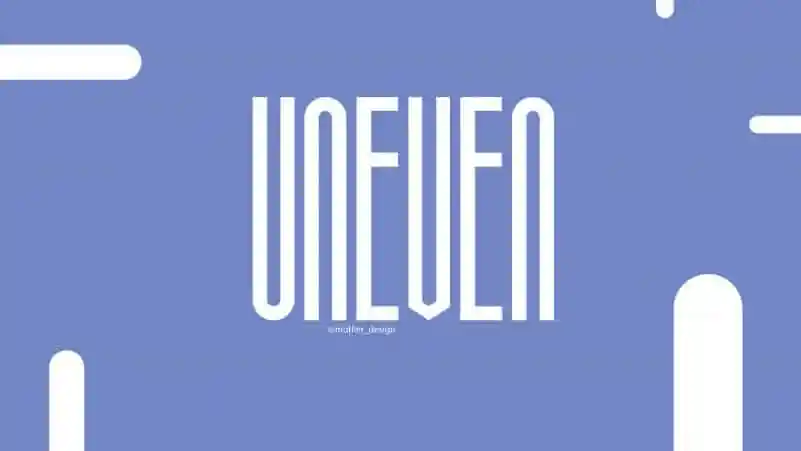
Introduzimos uma nova fonte de exibição, que é alta e densa. É uma fonte versátil que funciona incrivelmente bem tanto em grandes quanto em pequenos tamanhos. Esta fonte singular tem um design único, com linhas fortes e compridas, ideal para adicionar um toque diferenciado a qualquer projeto visual. Seja ela o título de um site ou o roteiro de uma história no vídeo game, certamente se destaca em qualquer contexto. Com ‘Uneven Font Demo’, criadores e designers podem explorar as infinitas possibilidades que esta fonte pode oferecer para personalizar suas criações de maneira única e estilizada. É a escolha perfeita para quem busca uma alternativa moderna à tradição, buscando criar um impacto visual inovador.